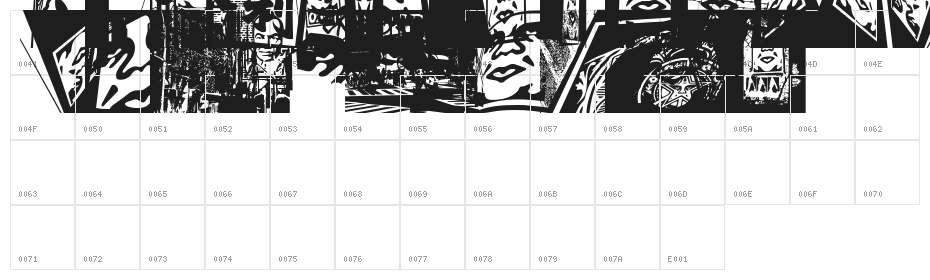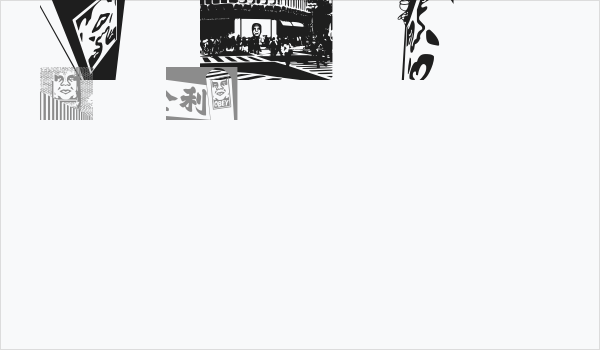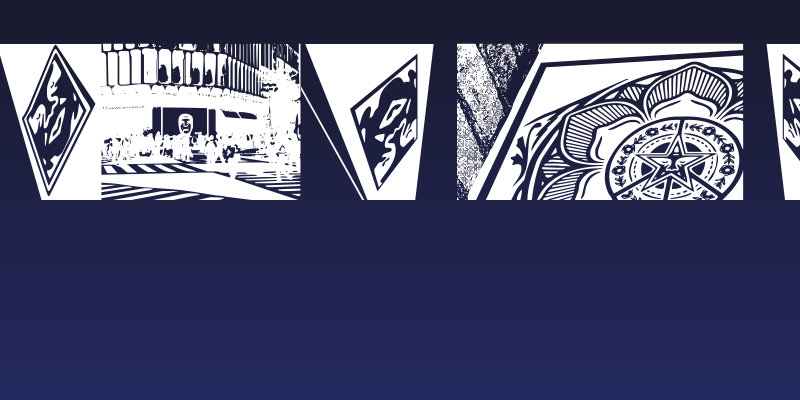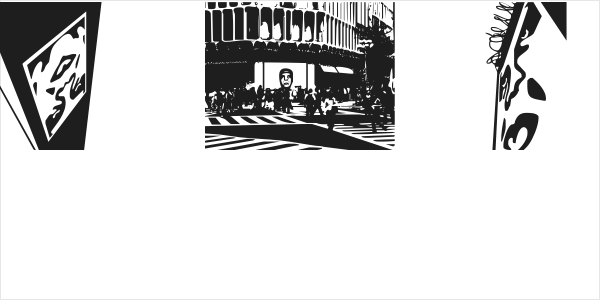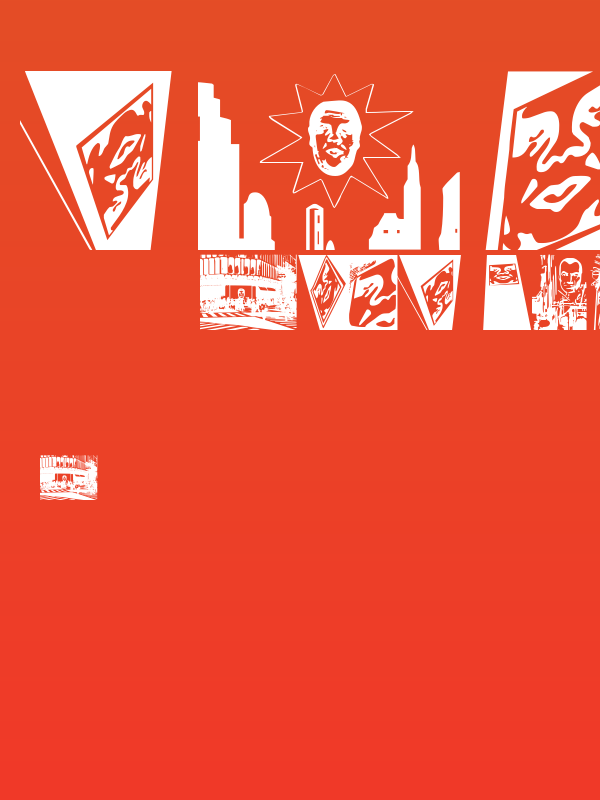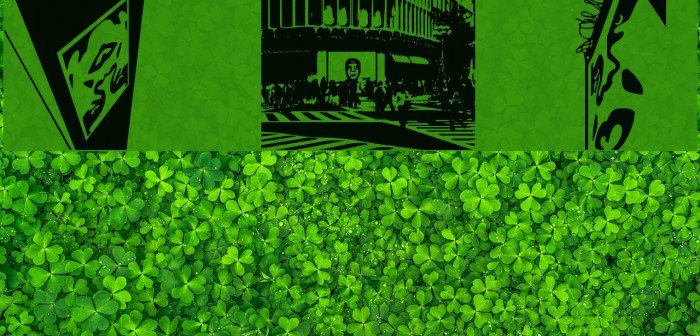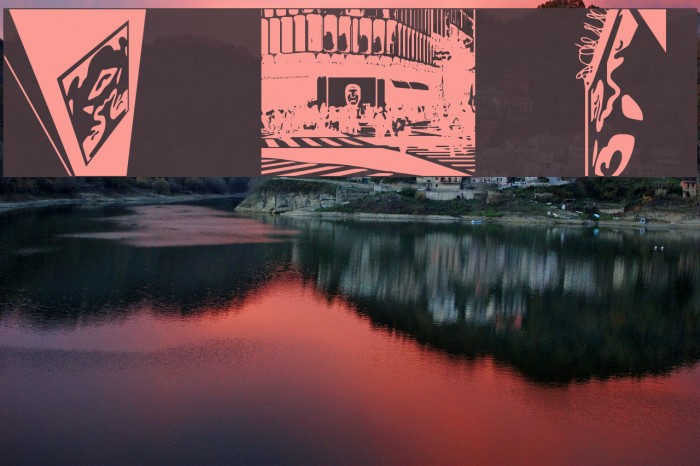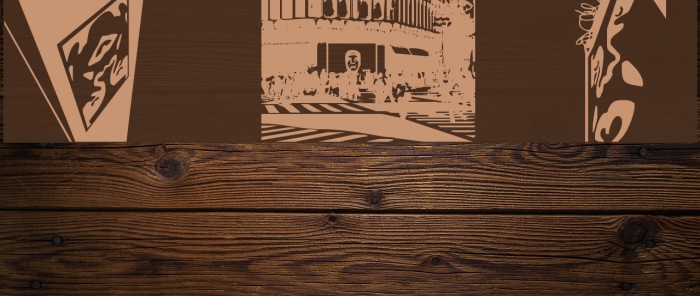
ObeyTownAlt Font
| Stile generale | Modern, Artistic |
| Caso d'uso | Headlines, Logos, Artistic projects |
| Progetti proposti | Ideal for posters, album covers, street art projects, and branding that requires a bold, artistic statement. |